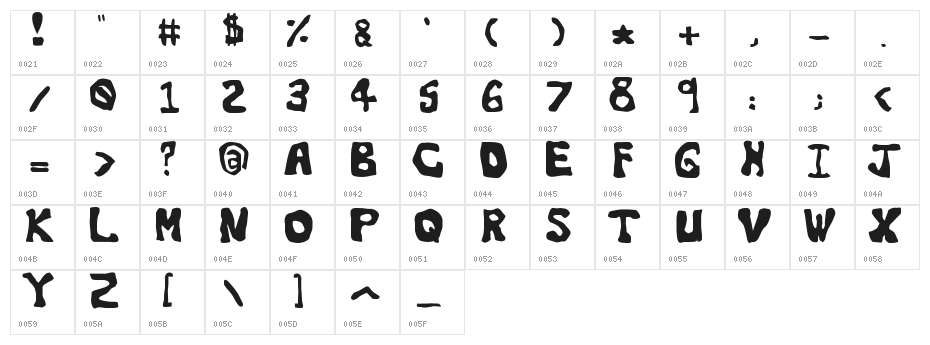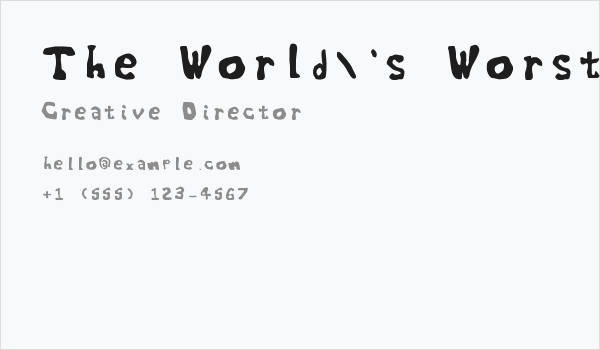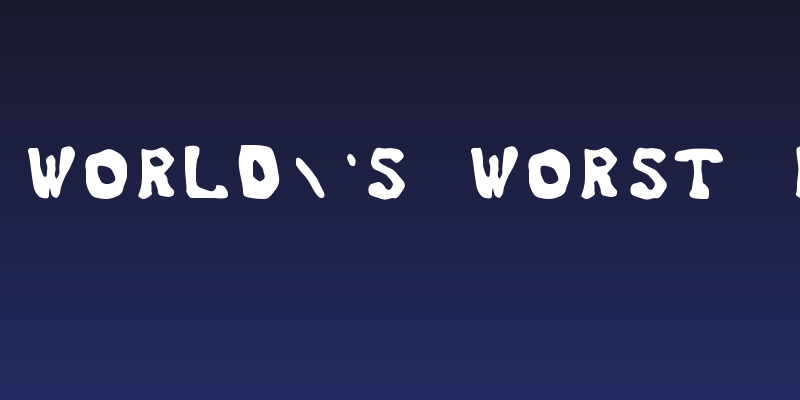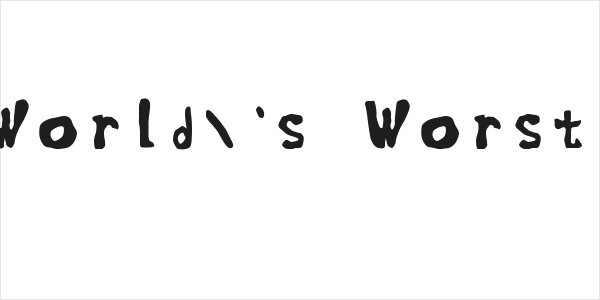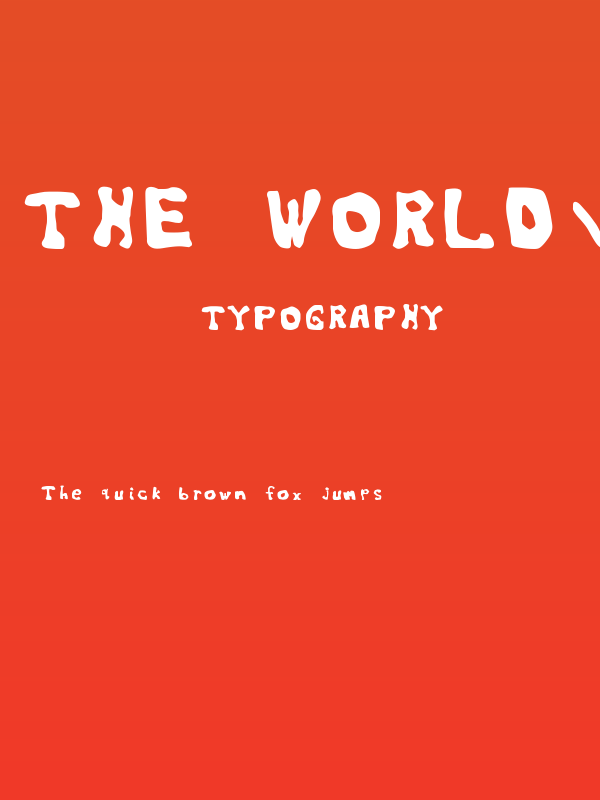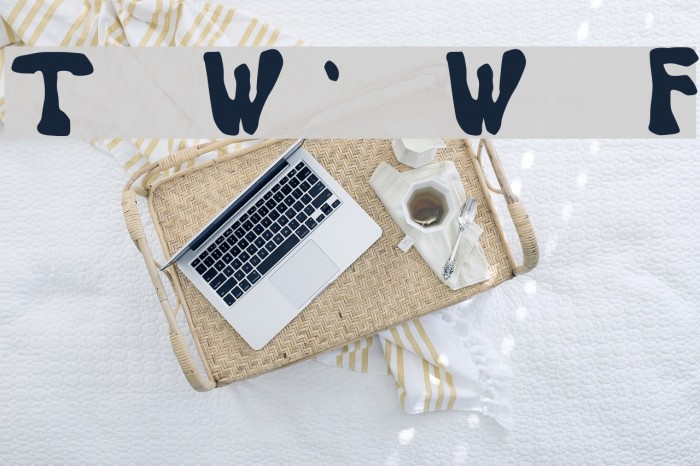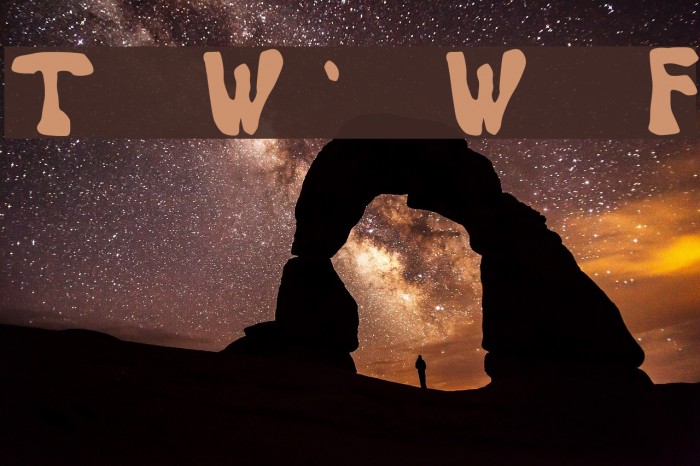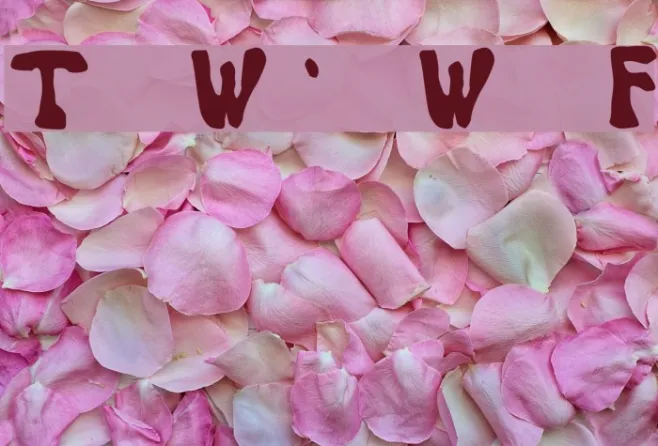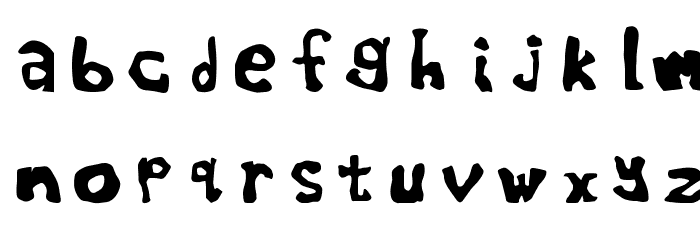
The World's Worst Font Font
| Stile generale | Playful, Whimsical |
| Caso d'uso | Headlines, Posters, Informal Invitations |
| Progetti proposti | Ideal for children's book covers, playful posters, or any project requiring a fun and informal touch. |